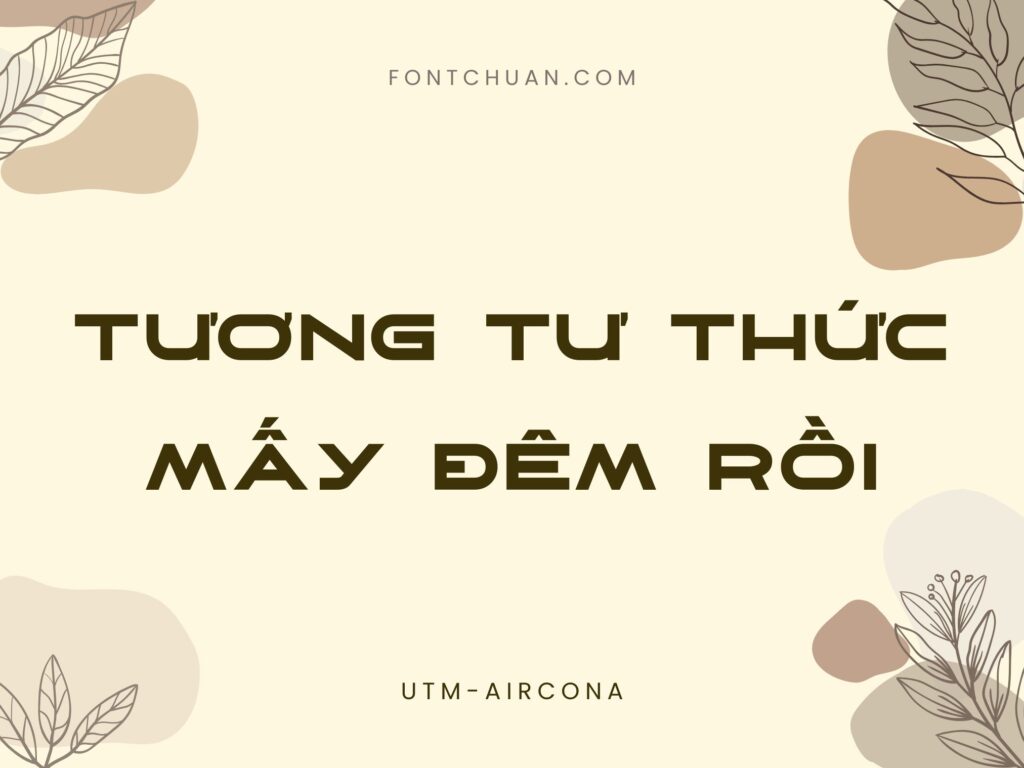
UTM Aircona là một kiểu chữ sans-serif hiện đại, được thiết kế bởi Michael Đinh Kiên và phát hành bởi Công ty TNHH Vitoen. Font này đã được Việt hóa, hỗ trợ đầy đủ tiếng Việt cùng hơn 100 ngôn ngữ khác. Thành viên của Font Chuẩn đã sưu tầm và chọn lọc font này nhằm đáp ứng nhu cầu đa dạng của bạn đọc và ứng dụng thực tế vào các dự án thiết kế.
UTM Aircona có cấu trúc chữ đơn giản, sạch sẽ với các đường nét gọn gàng và độ dày đồng nhất, tạo nên vẻ đẹp hiện đại và dễ đọc. Font này phù hợp cho các ứng dụng như thiết kế logo, tiêu đề, bao bì sản phẩm và các ấn phẩm in ấn. Các ngành nghề như quảng cáo, bất động sản, giáo dục và công nghệ có thể tận dụng UTM Aircona để tạo điểm nhấn độc đáo trong thiết kế.